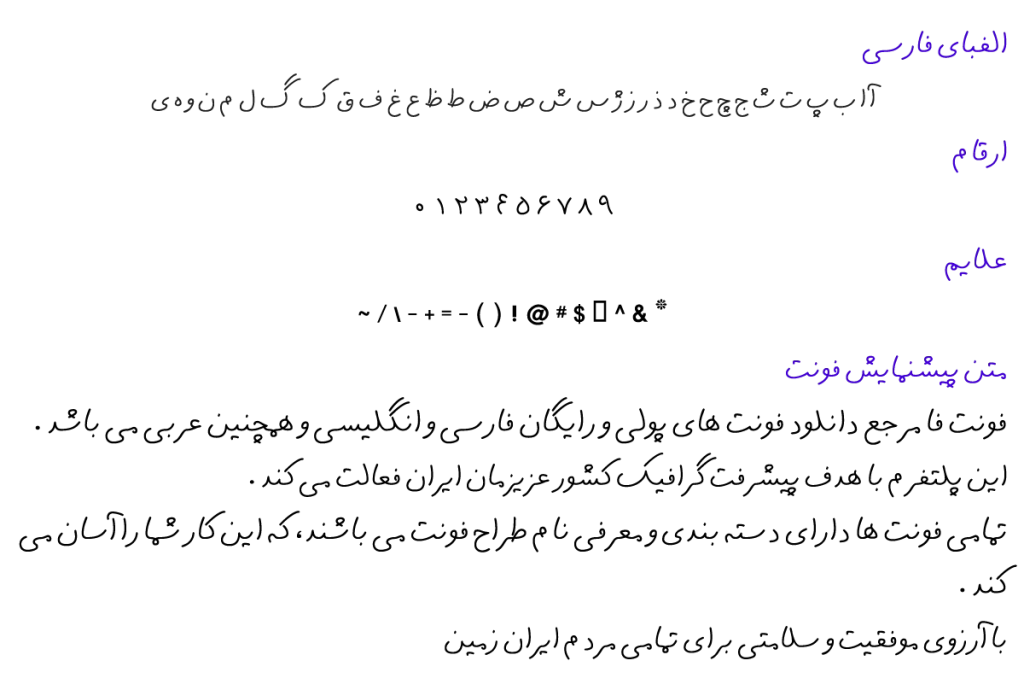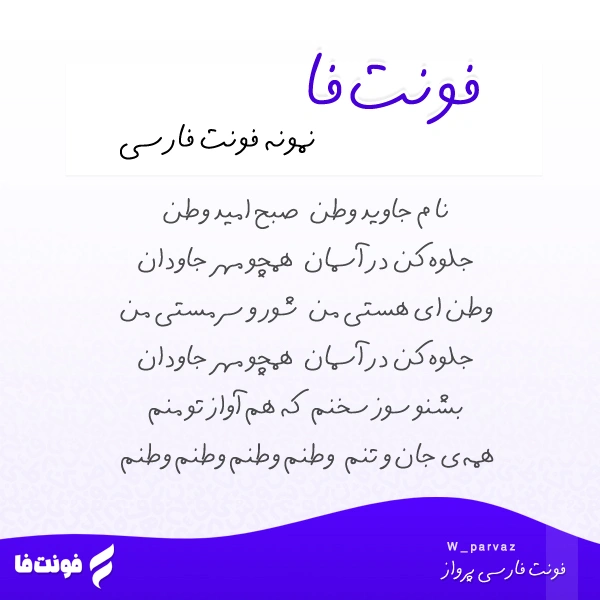
فونت فارسی پرواز – W parvaz
سال ساخت فونت: 1385
مجموعه فونت: فونت سری Mj
طراح فونت: نرمافزاری مریم نوع فونت: فونت دست نویس
توضیحات و معرفی فونت پرواز
فونت فارسی پرواز ( W parvaz ) از مجموعه فونت های سری Mj می باشد، و نیز نوع فونت دست نویس می باشد.
فونت خوشگل مربوط توسط نرمافزاری مریم در سال 1385 طراحی و ساخته شده است.
و نیز فونت W parvaz در یک وزن معمولی است.
- W parvaz Regular
در تصویر زیر، پیش نمایشی از این تایپ فیس را همراه با شعر زیبای فارسی میبینید.